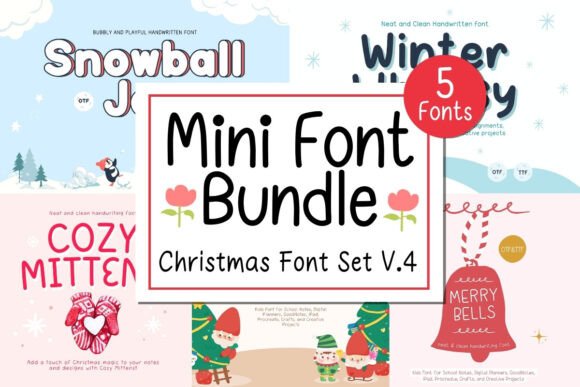
Mini Bundle Christmas Set V.4
Doğru tasarım öğelerini bulmak zor olabilir, ancak Mini Bundle Christmas Set V.4, çalışmanızı anında bir üst seviyeye taşıyan olağanüstü bir koleksiyon sunar.
İster İsteğe Bağlı Baskı (POD) ürünleri, ister düğün davetiyeleri veya sosyal medya grafikleri oluşturuyor olun, Mini Bundle Christmas Set V.4 ideal bir uyumdur.